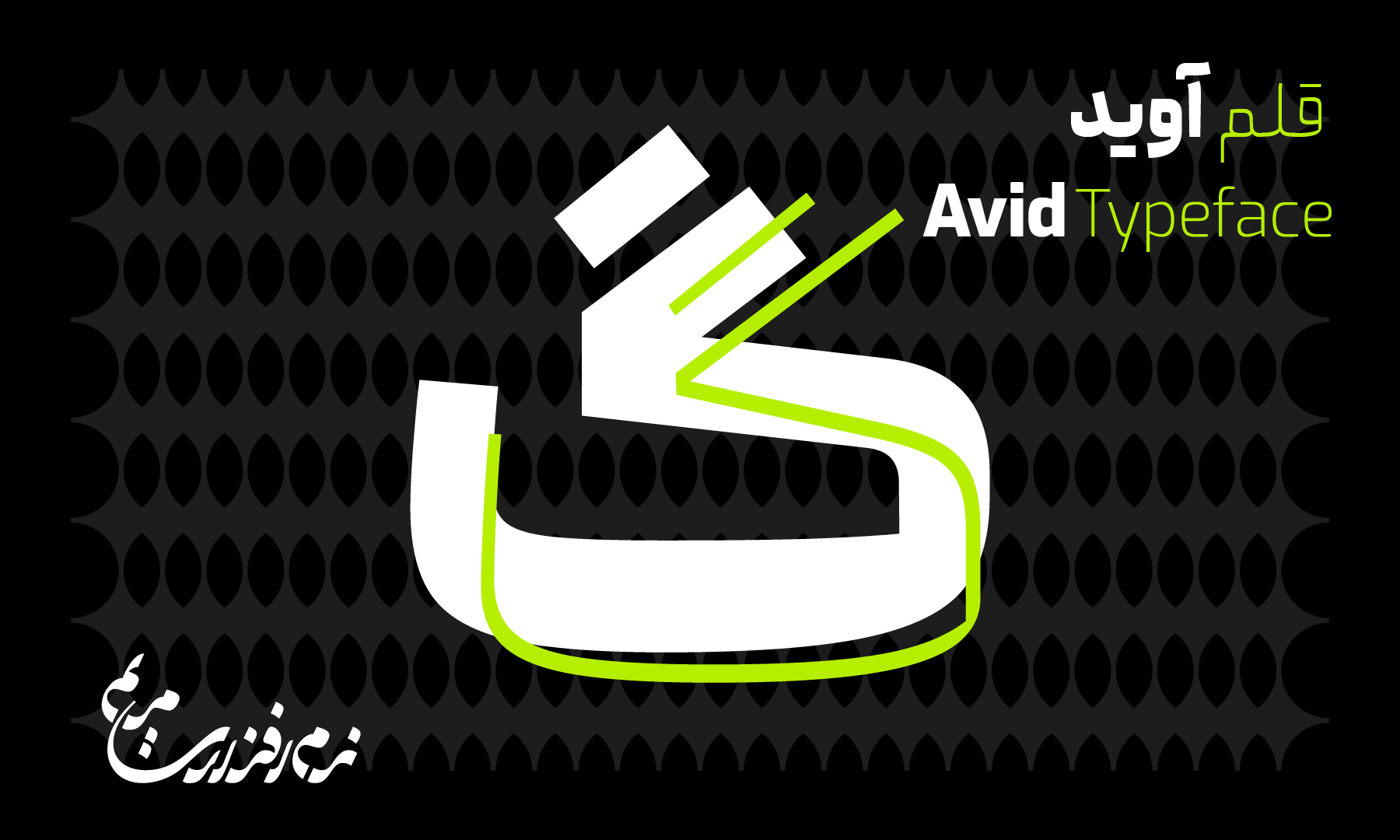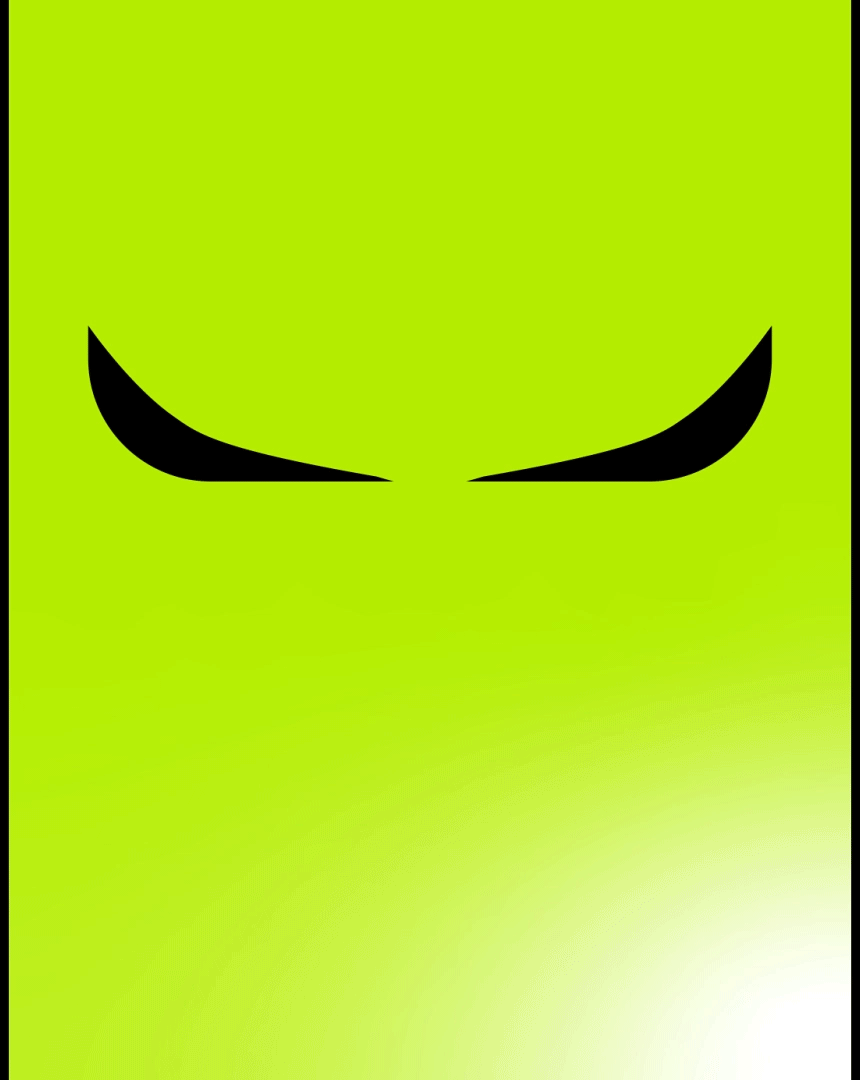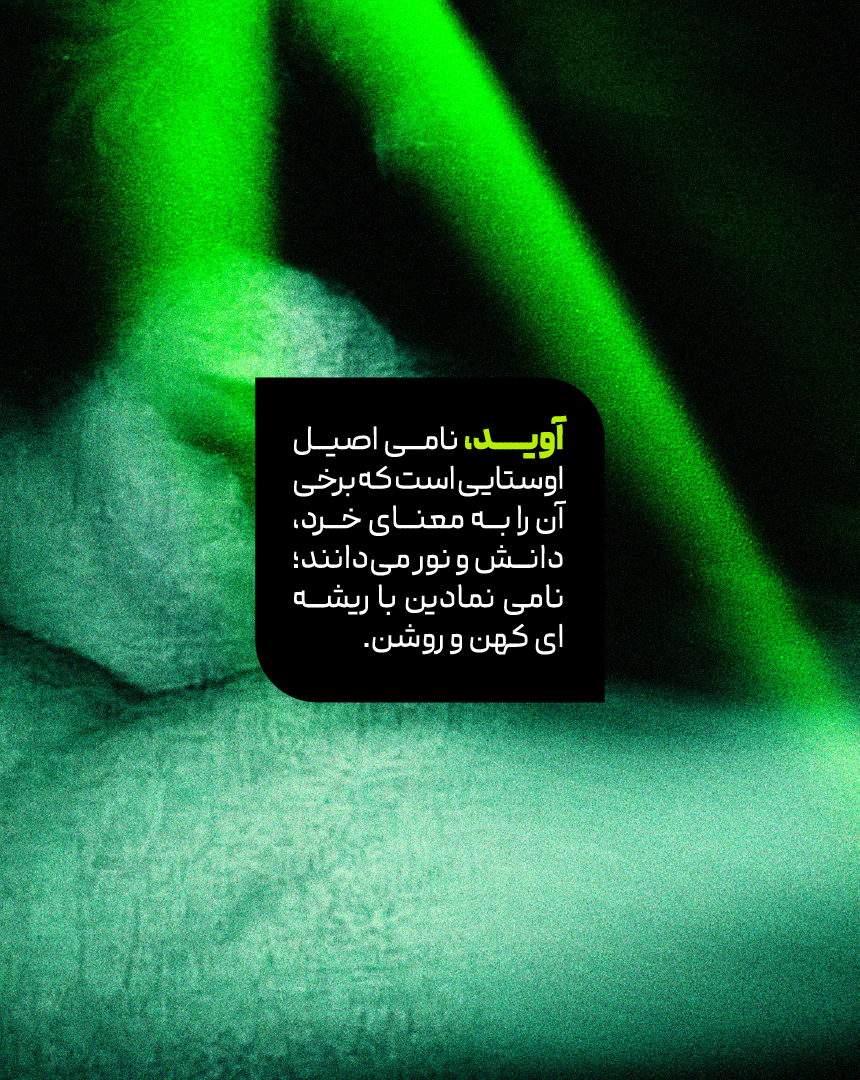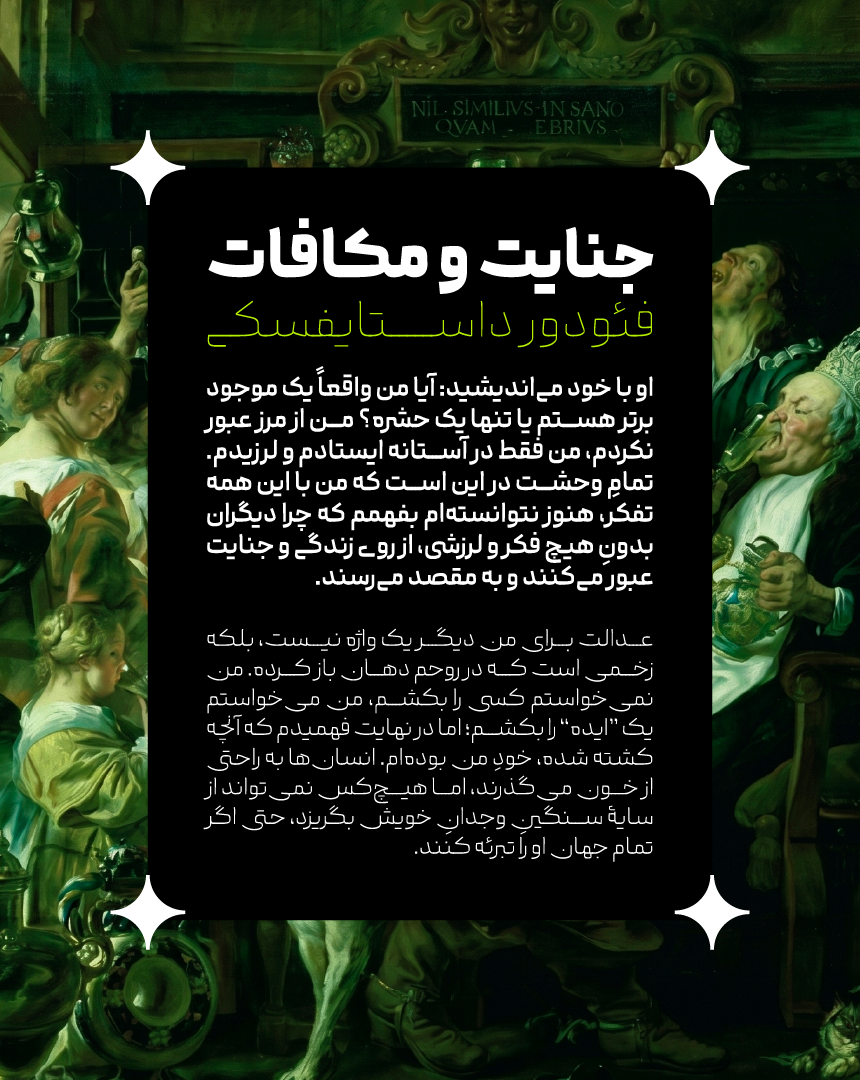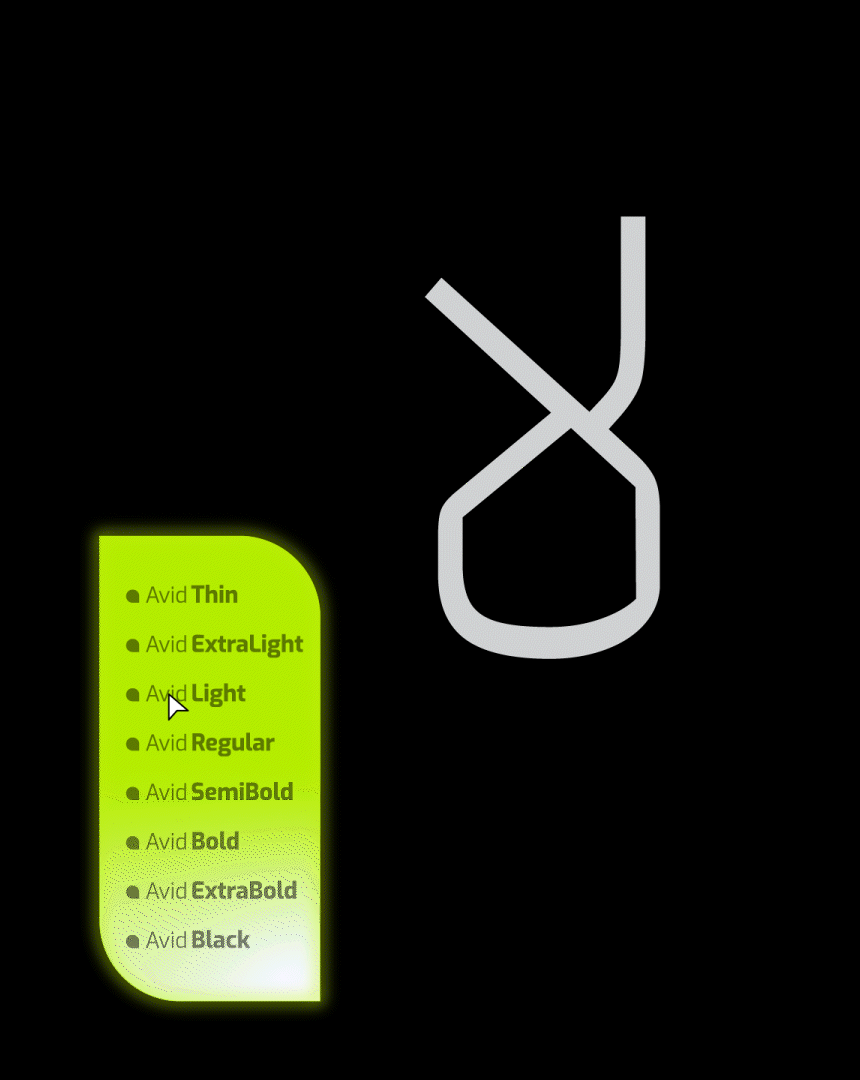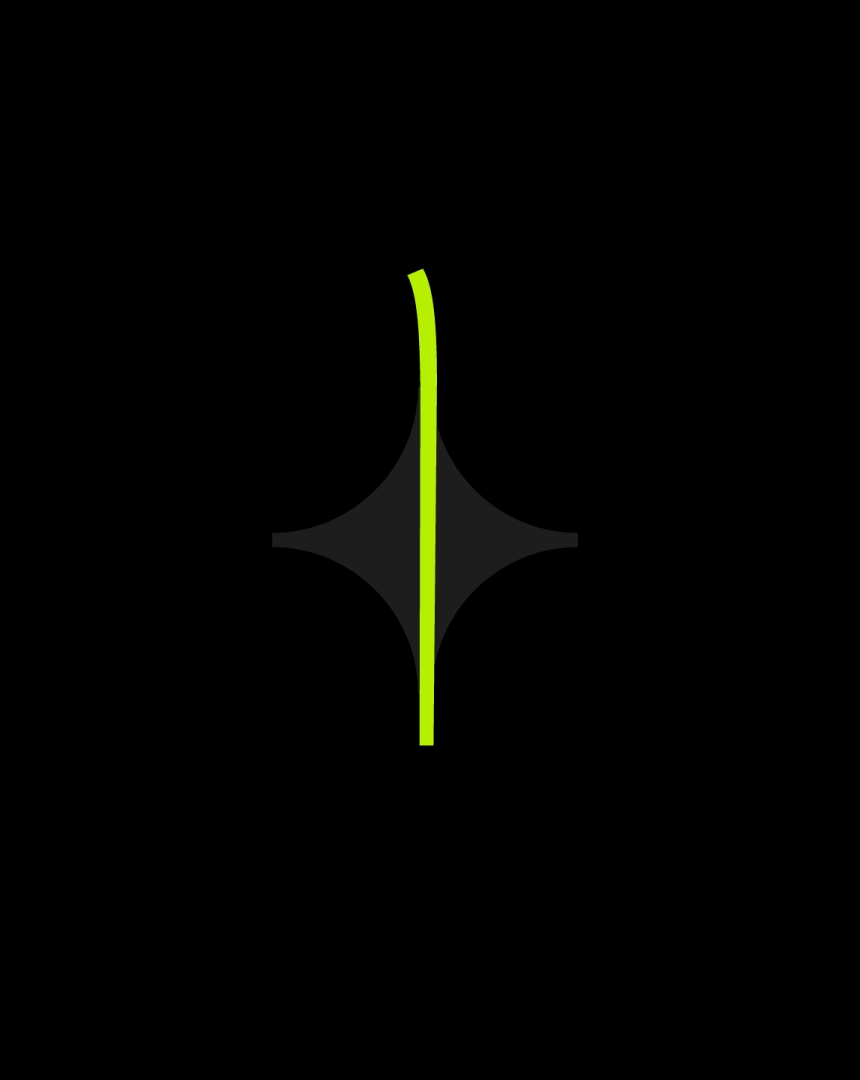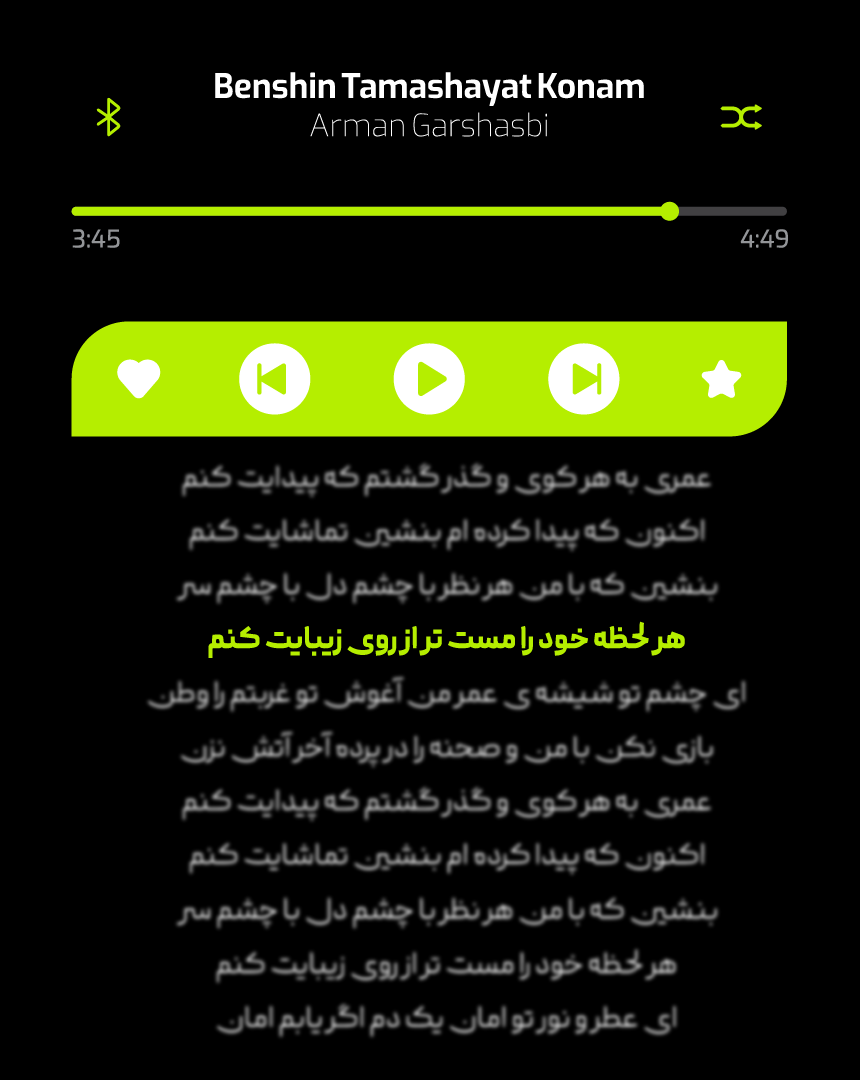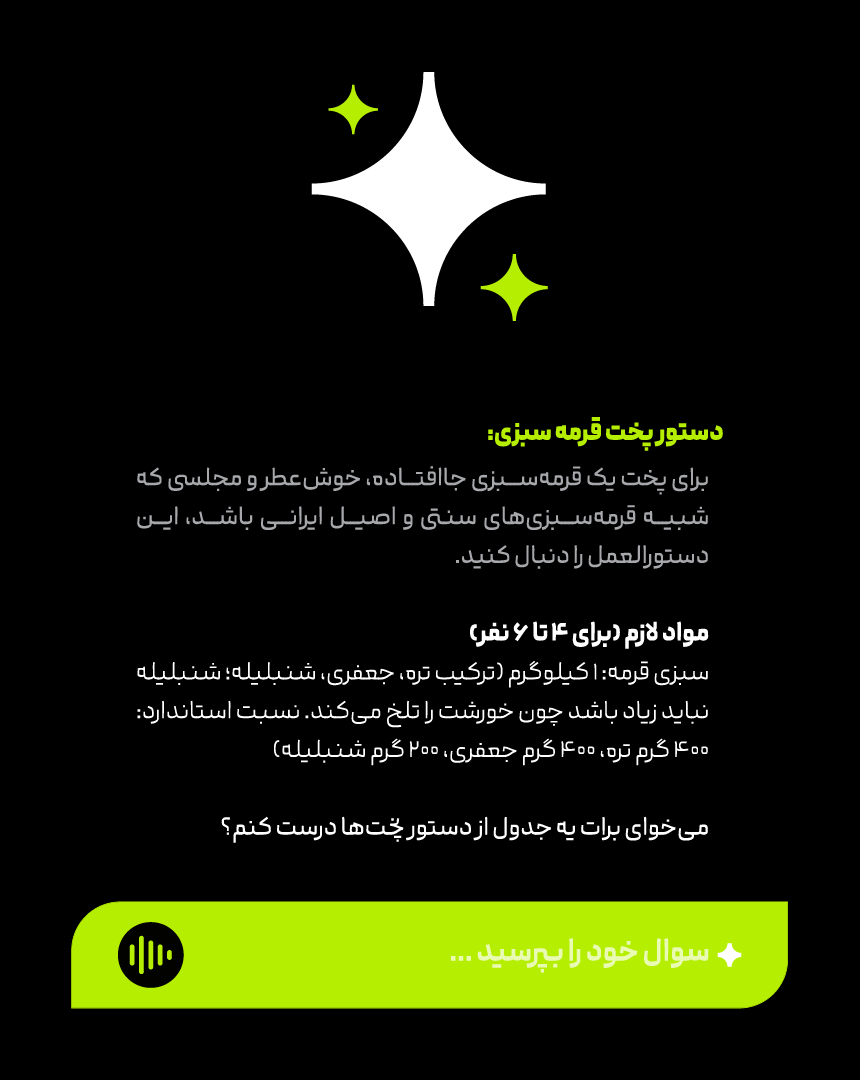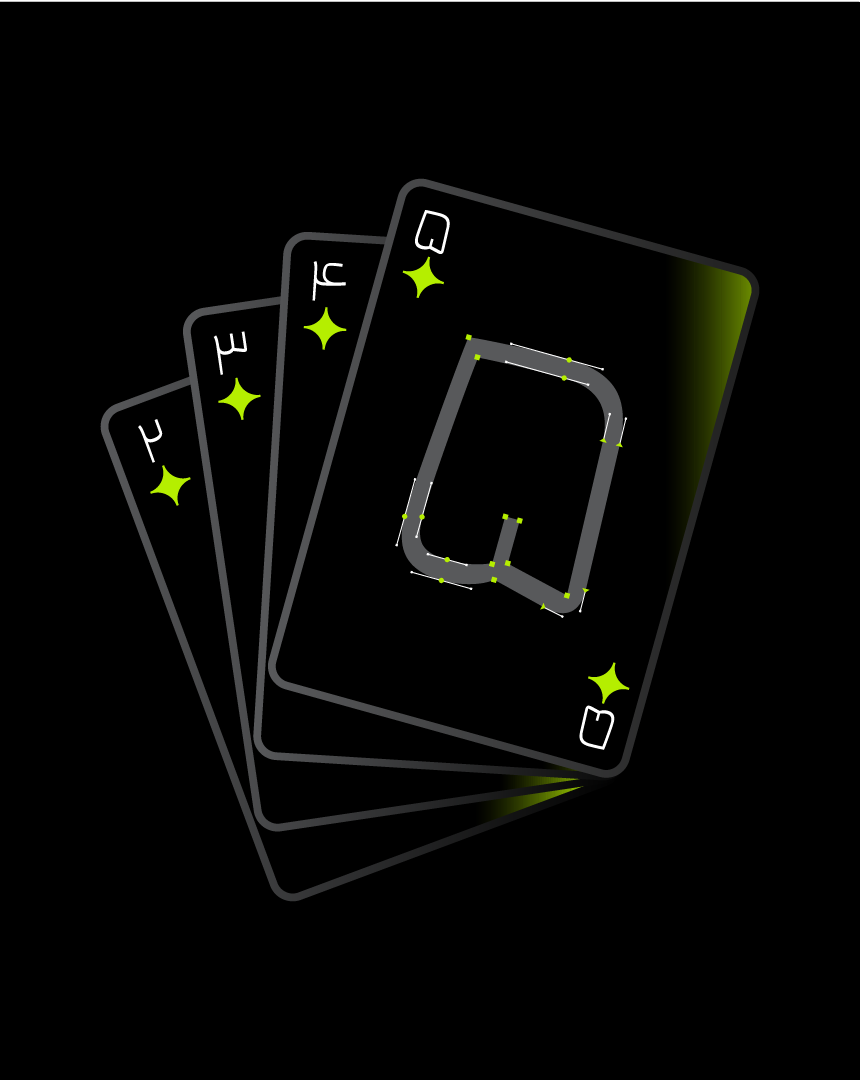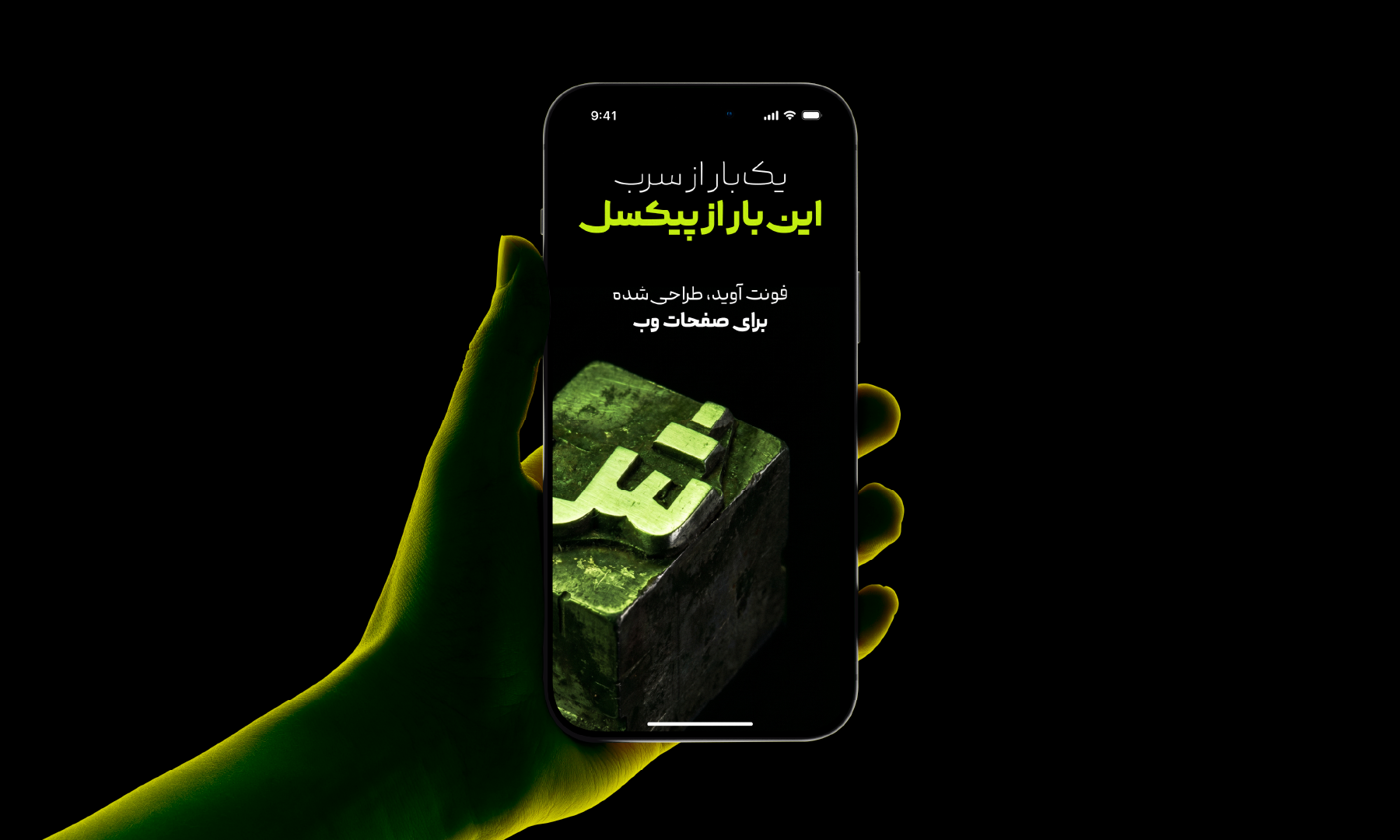
قلم آوید font Avid
قلم آوید
کاری از مقداد امینی
درباره قلم آوید
آوید تایپ‌فیسی است که با تمرکز بر فضای دیجیتال و نیازهای ارتباطی امروز طراحی شده است. این قلم در وب‌سایت‌ها، اپلیکیشن‌ها، رابط‌های کاربری و متن‌های کوتاه، عملکردی روان و خوانا دارد. خوانایی بالا در کنار شخصیت مدرن و متعادل، آوید را به انتخابی مناسب برای برندهای دیجیتال و پروژه‌های معاصر تبدیل می‌کند.
شخصیت آوید ترکیبی از سادگی، شفافیت و اعتمادبه‌نفس است؛ نه رسمی و سنگین و نه بازیگوش و غیرقابل‌اتکا. فرم‌های ساده و دور از تزئینات غیرضروری، حسی از صداقت و وضوح بصری ایجاد می‌کنند؛ ویژگی‌ای که به‌خصوص در رابط‌های کاربری، پیام‌های کوتاه و ارتباطات دیجیتال اهمیت دارد. به همین دلیل، آوید می‌تواند انتخابی مناسب برای برندهایی باشد که می‌خواهند مدرن، روشن و در عین حال قابل‌اعتماد به نظر برسند.
در طراحی آوید، حروف به ایستایی، تعادل و استحکام گرایش دارند. خطوط عمودی و زاویه‌های کنترل‌شده، حس ثبات را تقویت می‌کنند و هر حرف با قوام و توازن بر خط پایه می‌نشیند. این انسجام، ریتمی آرام و پایدار در ترکیب کلمات و سطرها ایجاد می‌کند و به حفظ یکپارچگی بصری متن کمک می‌کند.
در کنار این ساختار منظم، استفاده از انحناها و سطوح متناسب مانع از خشکی فرم‌ها شده است. نتیجه، تعادلی میان آرامش و پویایی است؛ حسی از جریان و حرکت که بدون برهم‌زدن ثبات بصری، به حروف زندگی می‌بخشد.
اتودهای اولیه آوید در دورهٔ طراحی حروف راست‌چین شکل گرفت. این ایده در ادامه توسعه یافت و با بازنگری و تکمیل جزئیات، به تایپ‌فیسی منسجم و کاربردی تبدیل شد؛ قلمی که برای حضور در فضای دیجیتال امروز طراحی شده است.
قلم آوید در جریان دورهٔ طراحی قلم راست‌چین و با هدف طراحی یک تایپ‌فیس اختصاصی برای یک برند شکل گرفت. نقطهٔ آغاز پروژه، رسیدن به قلمی با خوانایی بالا، اعتمادبه‌نفس و تعادلی میان آرامش و پویایی بود.
در مسیر طراحی، مفاهیم اولیه به فرم‌هایی ساده و هندسی تبدیل شدند؛ فرم‌هایی که ضمن حفظ پیوند با رسم‌الخط فارسی، بتوانند در اندازه‌ها و شرایط مختلف به‌خوبی خوانده شوند. هماهنگی میان حروف، کنترل فضای منفی، تناسب ارتفاع و عرض حروف و ایجاد تعادل میان استحکام و حرکت، از مهم‌ترین چالش‌های این مسیر بود.
آوید در طول توسعه بارها بازنگری شد. برخی فرم‌ها، برش‌ها و اتصالات تغییر کردند یا کنار گذاشته شدند تا ساختار حروف خلاصه‌تر، منسجم‌تر و کاربردی‌تر شود. پس از شش ماه اتود مستمر، نسخهٔ اولیهٔ قلم شکل گرفت و در پایان دورهٔ راست‌چین به نمایش عمومی درآمد.
با تصمیم به انتشار عمومی آوید، پروژه از محدودیت‌های یک قلم اختصاصی فاصله گرفت و امکان توسعهٔ آزادانه‌تر حروف و اتصالات فراهم شد. این مسیر پس از حدود یک سال طراحی، آزمون و اصلاح به نتیجه رسید و آوید به تایپ‌فیسی مستقل و کامل تبدیل شد.
طراح قلم
مقداد امینی
طراح گرافیک و طراح حروف فارسی
مقداد امینی، متولد ۱۳۸۲، در حوزهٔ طراحی گرافیک فعالیت می‌کند. مسیر حرفه‌ای او در سال‌های اخیر با همکاری در پروژه‌های متنوع شکل گرفته است.
بخش اصلی فعالیت و علاقهٔ او به طراحی حروف فارسی اختصاص دارد؛ تمرکزی که محور اصلی کار او بوده و همچنان ادامه دارد.